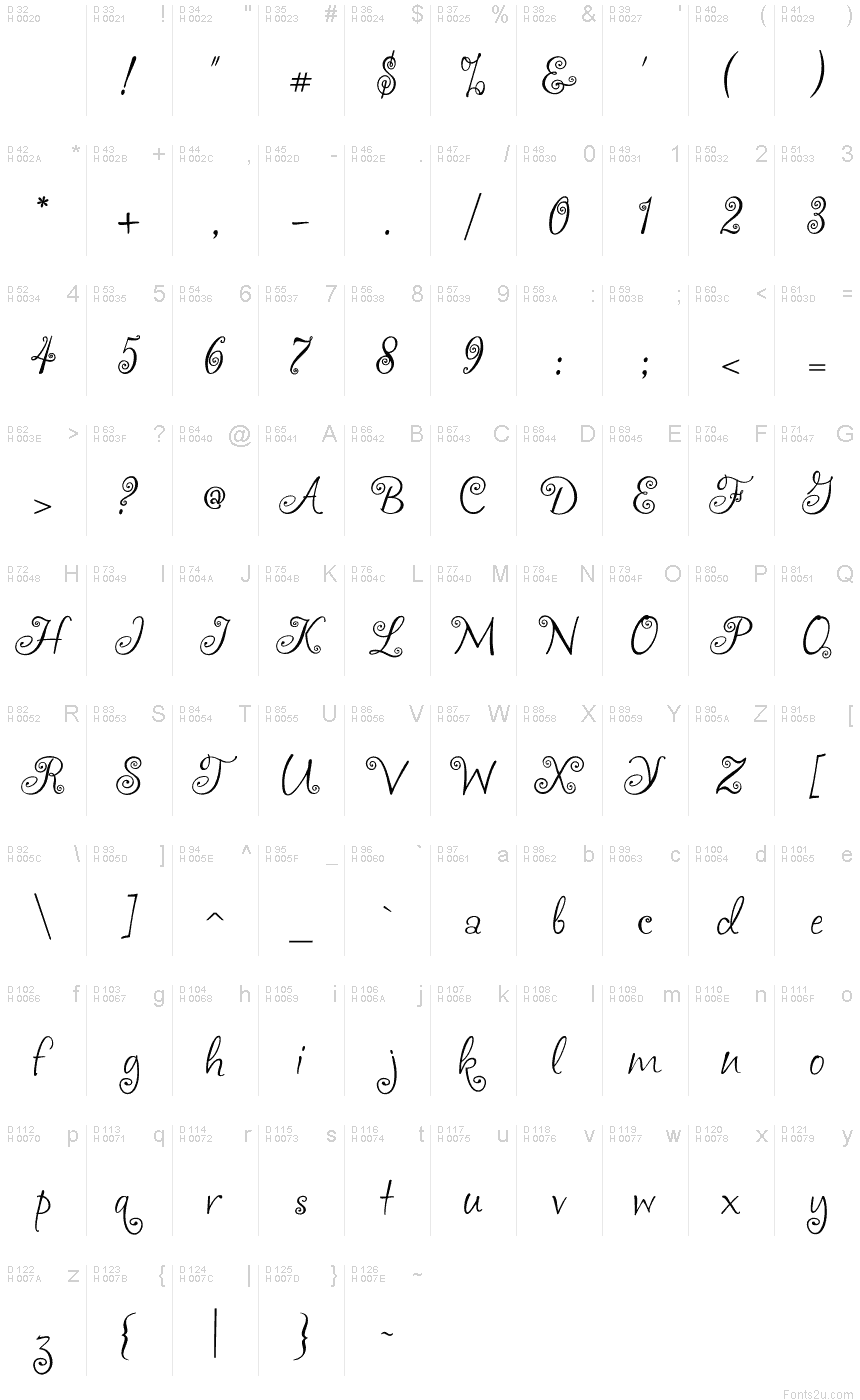
Aka Frivolity 是一款引人注目的展示字体,散发着奇思妙想的魅力。这款由 James Milligan 和 akaType 共同打造的曲线字体,以复杂流畅的笔触见长,线条优雅交织,营造出一种流动感与优雅气质。Aka Frivolity 既俏皮又不失精致的审美风格,使其能完美应用于各类设计场景,从版式设计到高端品牌塑造,均能轻松驾驭。
其独特的个性体现在细腻的变体和极具表现力的连字设计中,为字母增添了深度与神韵。这款字体的多功能性使其成为设计师的不二之选,无论是印刷品、数字媒体还是其他创意媒介,都能为您注入一抹精致与风采。